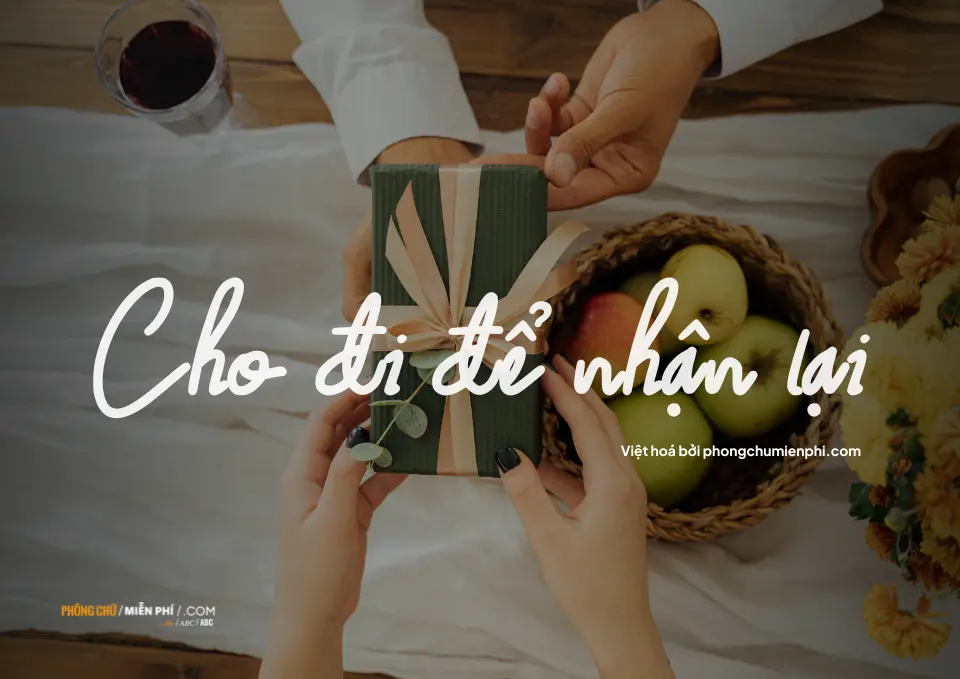
PCMP Ampunsuhu là phiên bản font việt hóa của “Ampun Suhu” – một font chữ monoline chữ ký thanh mảnh, mang đậm nét sang trọng và tinh tế. Với đường nét liền mạch và mềm mại, font này lý tưởng cho những dự án cần dấu ấn cá nhân, như thiệp mời, logo thương hiệu hay các ấn phẩm cho dịp đặc biệt.
Nguồn gốc & cảm hứng thiết kế
Ampun Suhu là một phông chữ chữ ký monoline, lấy cảm hứng từ nét viết tay tự nhiên, mượt mà. Mỗi đường nét đều được thiết kế liên tục, không đứt quãng, tạo nên sự liền mạch và mềm mại đầy cuốn hút.
Đặc điểm nổi bật
Kiểu chữ: Monoline script (chữ ký).
Hỗ trợ tiếng Việt: Việt hóa hoàn chỉnh với đầy đủ dấu và ký tự đặc biệt.
Nét chữ: Mảnh, uyển chuyển, gợi cảm giác sang trọng và cá nhân hóa.
Ứng dụng
Logo & thương hiệu: Tạo ấn tượng riêng biệt, tinh tế.
Thiệp cưới & thiệp mời: Mang đến vẻ đẹp lãng mạn, thanh lịch.
Poster & banner: Thu hút ánh nhìn với đường nét mượt mà.
Ấn phẩm cá nhân: Thích hợp cho chữ ký điện tử, watermark…
Ưu điểm nổi bật
Việt hóa chuẩn, giữ nguyên tinh thần thiết kế gốc.
Tạo hiệu ứng cao cấp và khác biệt cho dự án.